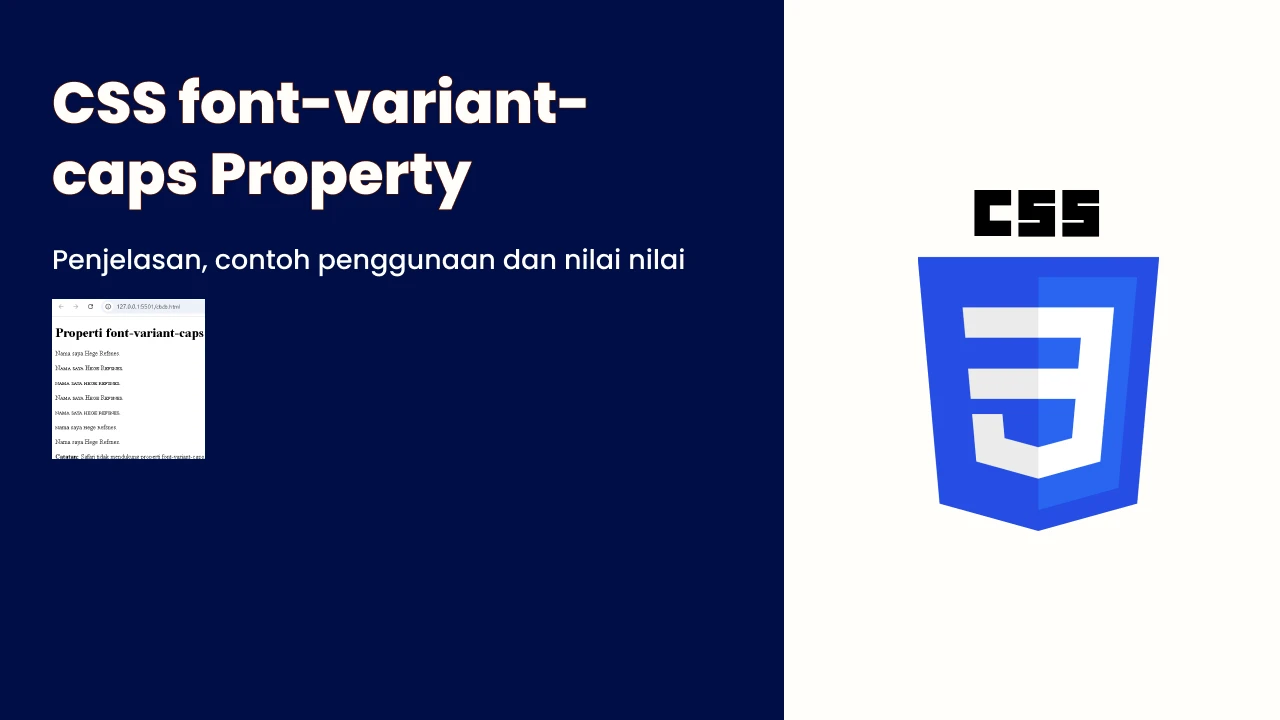
CSS font-variant-caps
Property
Contoh
Mengatur tampilan huruf kapital pada paragraf:
p.normal { font-variant-caps: normal; }
p.small { font-variant-caps: small-caps; }
p.allsmall { font-variant-caps: all-small-caps; }
p.petite { font-variant-caps: petite-caps; }
p.allpetite { font-variant-caps: all-petite-caps; }
p.unicase { font-variant-caps: unicase; }
p.titling { font-variant-caps: titling-caps; }
berikut hasilnya:
Definisi dan Penggunaan
Properti font-variant-caps
digunakan untuk mengatur gaya khusus huruf kapital dengan mengganti bentuk huruf (glyph) menjadi variasi lain, seperti huruf kapital kecil, huruf kapital mungil, dan lainnya.
Nilai Default: normal
Turunan: Ya
Dapat dianimasikan: Tidak
Versi: CSS3
Sintaks JavaScript:
object.style.fontVariantCaps = "small-caps";
Sintaks CSS
font-variant-caps: normal | small-caps | all-small-caps | petite-caps | all-petite-caps | unicase | titling-caps | initial | inherit | unset;
Nilai Properti
Nilai |
Deskripsi |
|
Menonaktifkan penggunaan bentuk huruf alternatif |
|
Menampilkan huruf kecil sebagai huruf kapital kecil |
|
Menampilkan semua huruf (besar dan kecil) sebagai huruf kapital kecil |
|
Menampilkan huruf kapital mungil (lebih kecil dari small-caps) |
|
Menampilkan semua huruf sebagai huruf kapital mungil |
|
Menampilkan gabungan huruf kapital kecil untuk huruf besar, dan normal untuk huruf kecil |
|
Menampilkan huruf kapital bergaya judul |
|
Mengatur nilai properti ke default |
|
Mengambil nilai dari elemen induknya |
|
Menghapus nilai, menjadikannya |